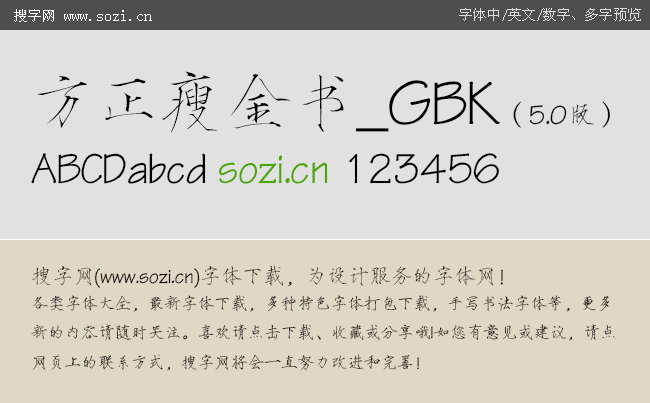
方正瘦金書(shū)-GBK
搜字網(wǎng)提供一款書(shū)法字體方正瘦金書(shū)-GBK字體下載,瘦金體為宋徽宗趙佶所創(chuàng),是書(shū)法史上的一項(xiàng)獨(dú)創(chuàng)。瘦金體運(yùn)筆飄忽快捷,筆跡瘦勁,至瘦而不失其肉,轉(zhuǎn)折處可明顯見(jiàn)到藏鋒,露鋒等運(yùn)轉(zhuǎn)提頓痕跡,是一種風(fēng)格相當(dāng)獨(dú)特的字體。適合字貼、招貼、書(shū)法畫(huà)冊(cè)設(shè)計(jì)應(yīng)用。